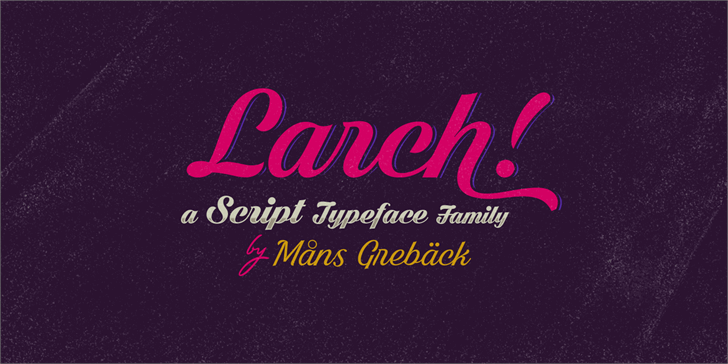
A Shaded Larch Font é uma deliciosa escolha para aqueles que buscam uma mistura suave e sofisticada entre linhas elegantes e tons matizados, oferecendo um toque especial à sua tipografia. Criado pelo designer Hamilton, este fonte de escrita é ideal para designers gráficos que procuram uma fonte de caligrafia única e versátil. Com seus traços suaves e nuances sofisticadas, a Shaded Larch Font proporciona um toque elegante a qualquer projeto. Para adquirir uma licença comercial desta fonte, visite: http://www.mansgreback.com/larch. Esta fonte é perfeita para quem busca uma aposta segura em design gráfico, sem dúvida.